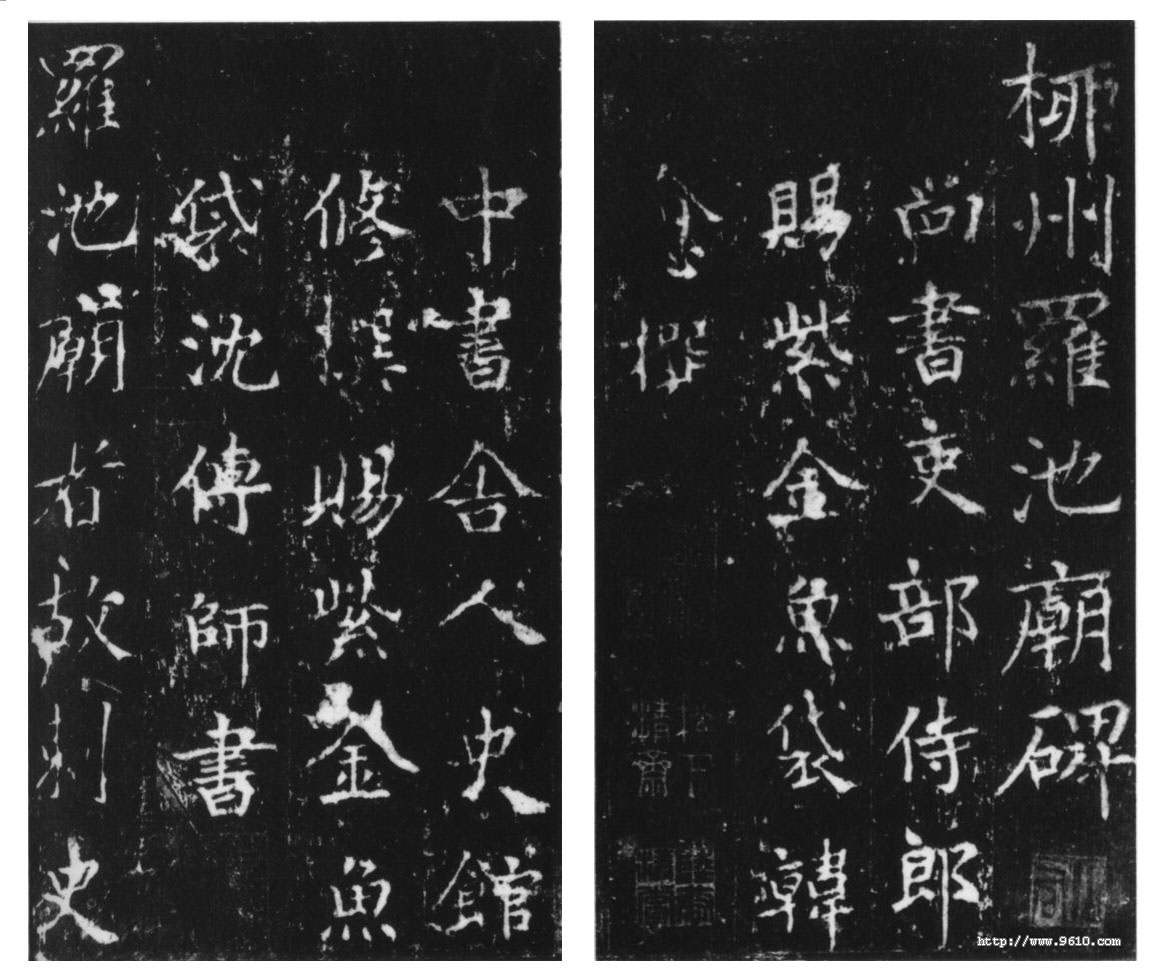
沈传师
沈传师简介
字子言,苏州吴县人,唐德宗贞元(785---805年)末举进士,累迁太子校书郎,翰林学士,中书舍人,湖南观察使,宝历元年(825年)拜为尚书右丞,吏部侍郎。旧唐书有传。
关于沈传师的书法,朱长文在《续书断》把他与虞、欧、褚、柳等并列为妙品。说他“正、行书皆至妙品。存于翠琰、爽快骞举,如许迈学仙,骨轻神健、飘飘然欲腾霄云”;宋代的米芾眼界与自视甚高,曾对颜的真书多有微词及至他人书法也极少嘉许,然在见沈氏书法时,却大为推重,谓沈氏书法“如龙游天表,虎踞溪旁,精神自若,骨法清虚”。说明沈传师在唐代也是一位非常出色的书家。有一则故事,说米芾曾游湘西道林岳麓寺,由于他非常喜爱沈传师书法,即向寺里主持恳求能否将沈氏所书的《游道林岳麓寺诗》借观,寺僧慕其大名及爱其“颠狂”,遂借之以予,哪知这米颠,爱不释手。想据为己有,竟“一夕张帆携之遁去”,使得寺僧不得不急忙向官府告发,才得以追回,想见老米酷爱沈氏书法的程度及在其心中的位置。
作品欣赏:柳州罗池庙碑
《柳州罗池庙碑》为沈传师53岁时所书,碑文由大文学家韩愈撰写,纪念颂扬柳宗元被贬任柳州刺史所做的政绩。碑立于罗池庙内,碑石早已不存,至于何年遭毁,现无从查考,今所见拓本乃据清何绍基旧藏宋拓孤本一册影印。浏览此碑书法,气息清劲圆润、骨法神健,结字虽较为瘦削,然挺健秀朗,肉藏于筋,略无枯瘠之垢病。乍一看,近似柳(公权)书,但细察与柳书有着根本的区别,那就是柳书中宫过于内敛,紧缩得让人心中发慌,沈书却无此特征,虽然中宫也稍作内敛,但总体来说,还是属于较宽松的。另一个与柳书不同点即在结构上,沈氏书法结体多呈左低右高势,且略向右欹侧,当然,此碑书法也确实存在与柳氏书法相同的地方,其中竖弯钩、点、撇、捺、悬针竖等用笔和一些字的结体如“言“字旁,“诏”、“柳”、“师”、“不”等与柳书如出一辙,究竟是谁影响了谁?请看王铎跋此拓本的一句话“沈书寡觌,本虞永兴,柳诚悬、欧率更,合为一家”。如果王铎的话可信,显然沈师承了柳,然据《旧唐书》柳公权本传推测,柳(公权)小于沈传师九岁,同时,本传有一段话也耐人寻味,“公权初学王书,遍阅近代笔法,体势劲媚,自成一家”。说不定这“近代笔法”里就包括沈传师在内。如捡柳书《李晟碑》与《罗池庙碑》   >>更多详细